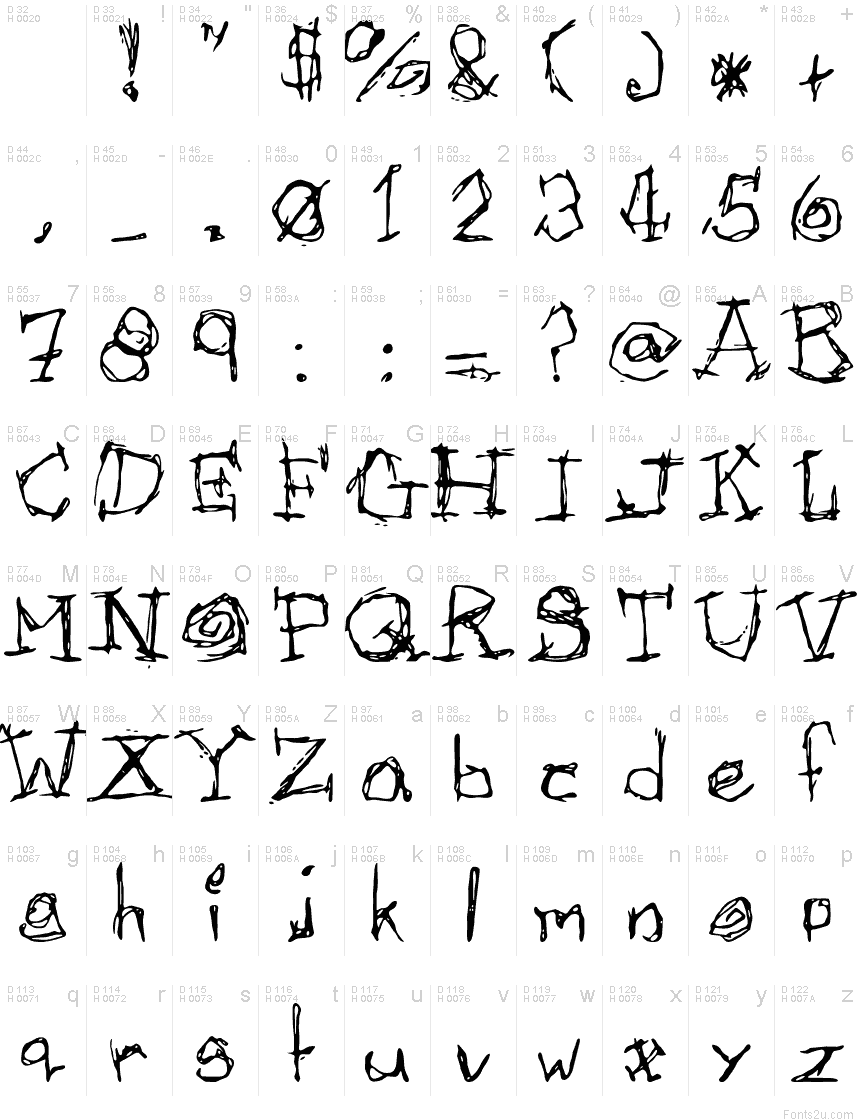
Afectionless di Largo è un carattere trash script gratuito che sembra graffiato su un muro con un pennarello quasi secco. Curve irregolari, tratti frastagliati e sovrapposizioni di inchiostro conferiscono a ogni parola un'energia frenetica e improvvisata, pur rimanendo leggibile a dimensioni medie. È un font crudo e rumoroso, come una nota scarabocchiata sul retro di un volantino a tarda notte, che aggiunge consistenza e tensione senza bisogno di grafiche extra.
Con Afectionless, puoi spingere i tuoi poster, titoli horror, copertine di album punk o metal, fanzine, grafiche streetwear e loghi di videogiochi verso territori più oscuri e caotici. Questo font gratuito dà il meglio di sé se lasciato respirare in titoli grandi, abbinato a un carattere sans serif stretto e semplice per il testo principale, mantenendo la grinta concentrata dove colpisce di più.